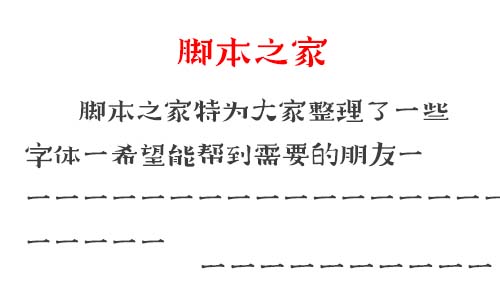
苏州精致体
苏州精致体呈开放式的笔画布置,横笔笔端作圆弧形翘起,撇点灵动秀气、字形优美圆润,整体借鉴了宋体印刷字体又不拘于常规,展现随性现代的美感,欢迎喜欢苏州精致体的朋友前来下载使用。
字体介绍
在追随经典的同时寻找精致的格调,通过比划间微妙破笔、加减粗细,拙笔来体现精致生活下的四味生活,再将苏州人对追求的精致融为一体,创新崭新时代精致的内涵。
好的字体设计从来不囿于字体设计,而是与文化底蕴、情感内涵一脉相承。
“苏州精致体”是苏州新希望地产与瞿子竣设计师一同开启苏州精致文化想象力的钥匙,它是苏州语言在文化领域的一次重要实践,以更为诗意的方式去传递苏州的艺术文化,而在“苏州精致体”这一文化符号的背后,亦是苏州新希望地产对苏州精致理念的无尽探索。
一横一竖
代表着始终刻在苏州城市肌理与生命骨血里的精致icon
一撇一捺
代表着始终都深植于苏州新希望地产步履苏州的每一步
苏州新希望地产借助“苏州精致体”的全新上线,亦将酿造生活的美好新章,开拓苏州文化的更新版块,不止是精致,更是恒久的深情。